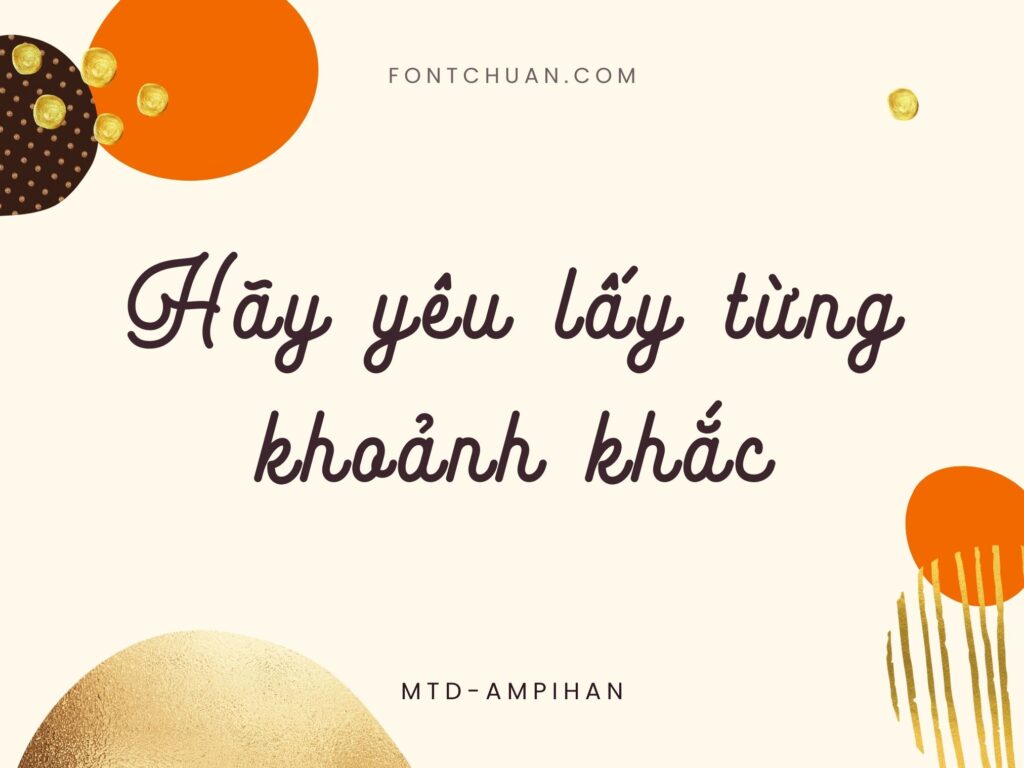
Font Ampihan là một kiểu chữ viết tay độc đáo, mang phong cách hiện đại và sáng tạo. Với các nét chữ mềm mại và uyển chuyển, Ampihan mang lại cảm giác thân thiện và gần gũi cho các thiết kế.
Phiên bản Ampihan đã được Việt hóa bởi Mộc Hạ, hỗ trợ đầy đủ tiếng Việt cùng hơn 171 ngôn ngữ khác, mở rộng khả năng ứng dụng trong thiết kế đa ngôn ngữ. Font này đã được thành viên Font Chuẩn sưu tầm và chia sẻ, đáp ứng nhu cầu của cộng đồng thiết kế. Với thiết kế bao gồm các ký tự viết tay tinh tế và đa dạng, Ampihan phù hợp cho các ứng dụng như thiết kế logo, thiệp mời, bao bì sản phẩm và các ấn phẩm quảng cáo. Các ngành nghề như quảng cáo, giáo dục, công nghệ và ẩm thực có thể tận dụng font này để tạo ra thiết kế ấn tượng và thu hút.